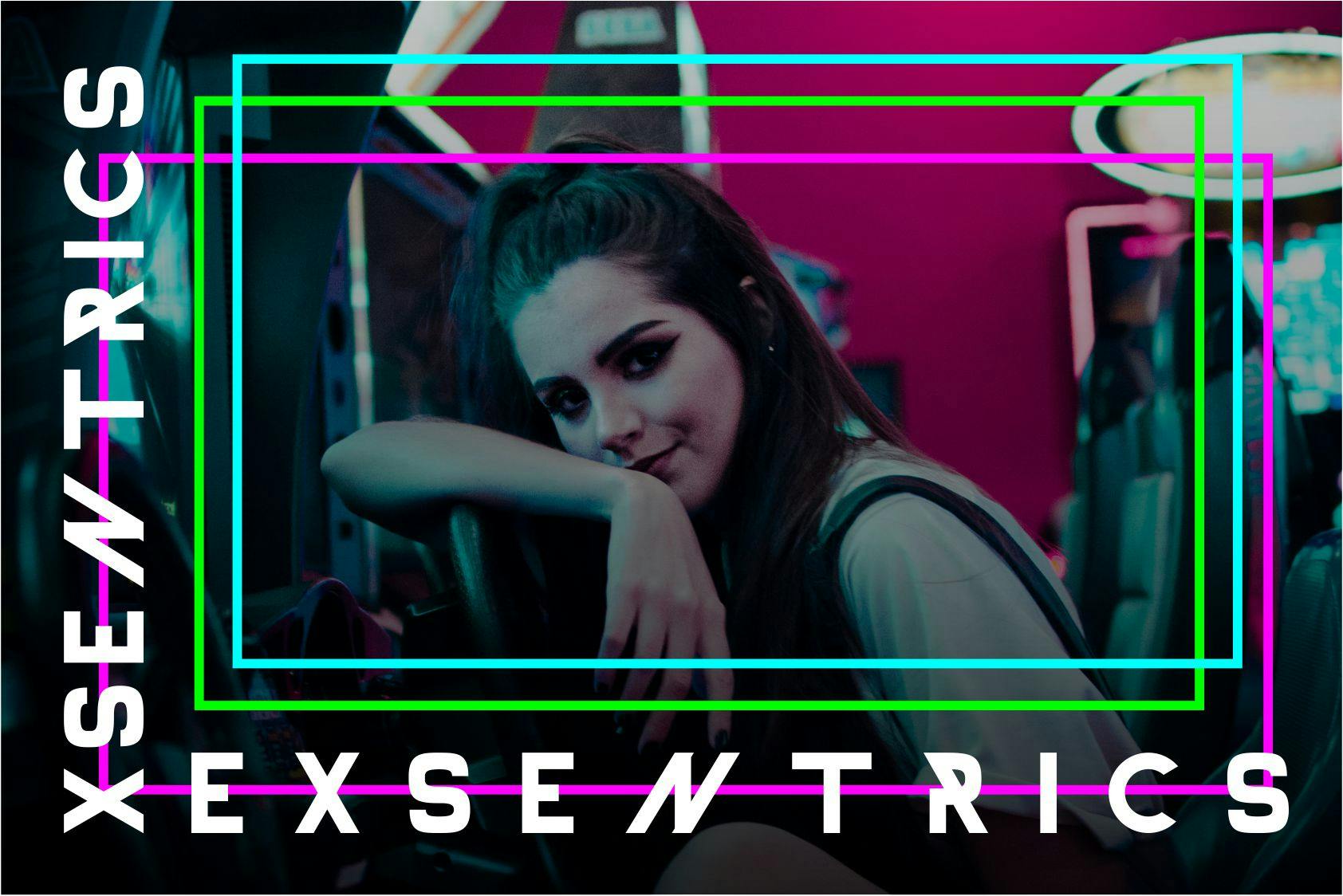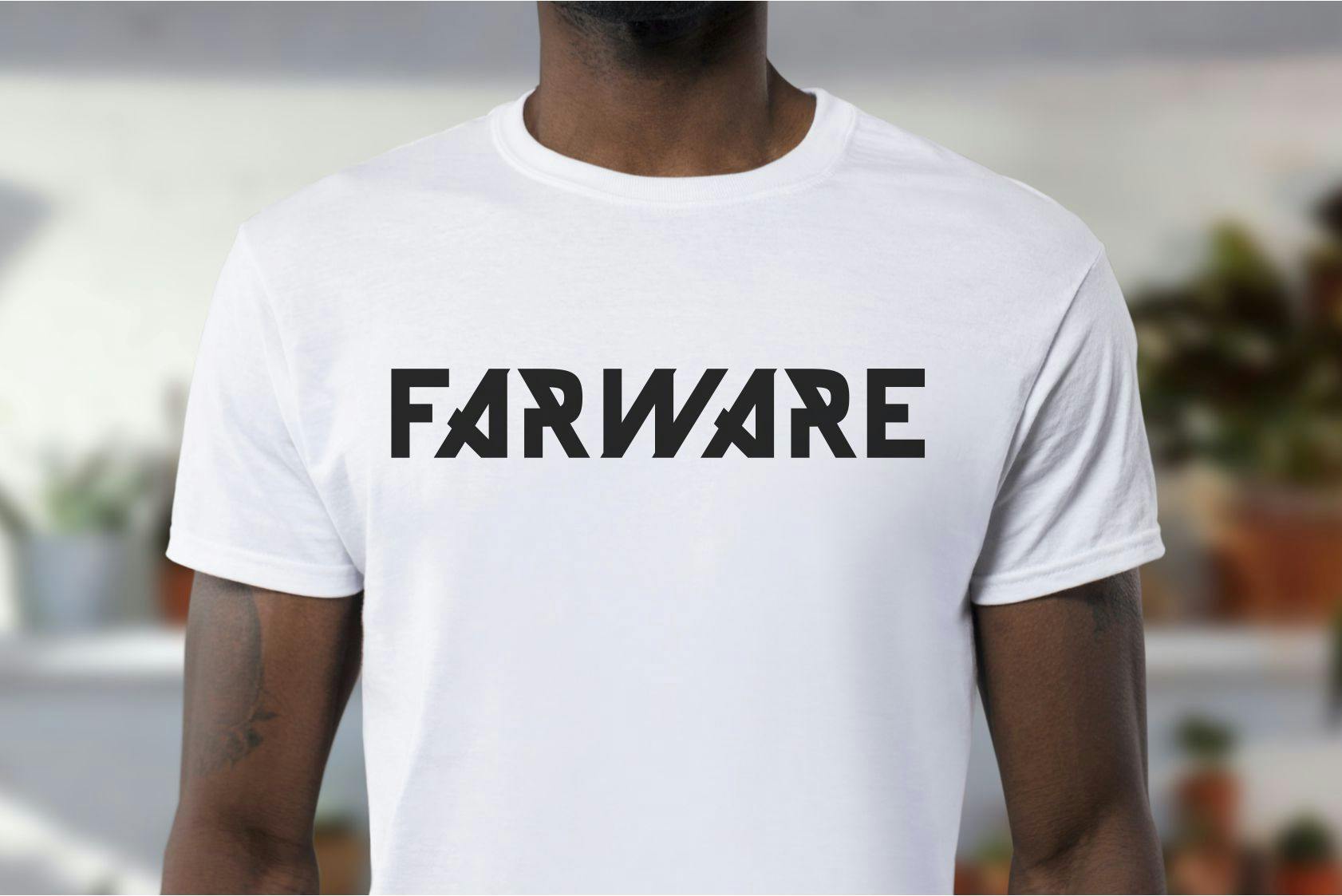
فونت Farware شامل حروف بزرگ، اعداد و مجموعهای وسیع از نشانهگذاری است. این فونت sans serif با سبک مدرن طراحی شده و برای پوسترها، طراحی وب، برندینگ، illustrations، نشانها و برخی کارهای دیگر مناسب است.